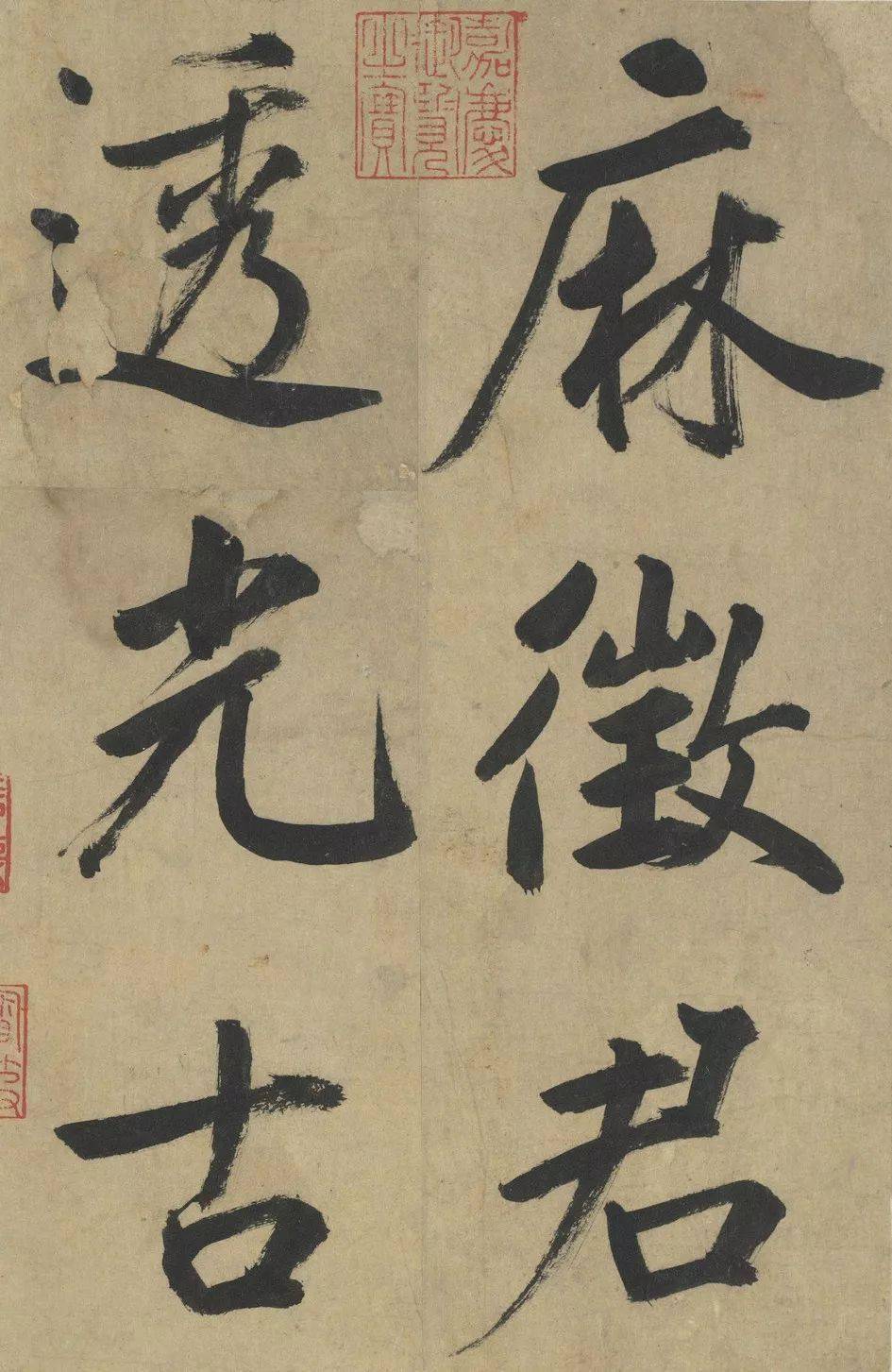
字体全名: 汉标鲜于枢透光古镜歌
字体简介: 下载须知:本字库非标准GB2312字库。本字库只包含了鲜于枢《麻徵君透光古镜歌》真迹上的“203个字”。鲜于枢《麻徵君透光古镜歌》 纸本,30.5 x 19.8cm 台北故宫博物院藏。《麻徵君透光古镜歌》似乎不经意于每一笔画的精美,而着力于每个字的整体气势与形象的创造。苏轼曾说过:“大字难于结密而无间,小字难于宽绰而有余。”此幅大字称得上“结密无间”,而且越往后写的越好,运笔着墨均达到完美的程度。总体看,此幅大字体势规整,气势恢弘,是鲜于氏大楷书的典型之作。